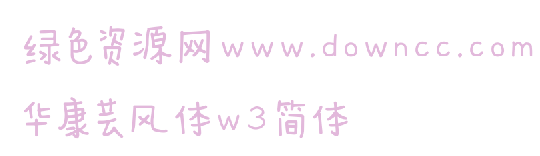
華康蕓風(fēng)體w3 簡(jiǎn)體是一款活潑可愛(ài)風(fēng)格的字體。小編搜羅了全網(wǎng)才找到的華康蕓風(fēng)體簡(jiǎn)呢~歡迎大家來(lái)下載這款萌萌噠的字體。
華康字體以其清新自然的設(shè)計(jì)、繼承也創(chuàng)新的完美結(jié)合、全球觀的推廣營(yíng)銷,使得其贏得相當(dāng)比例的用戶。